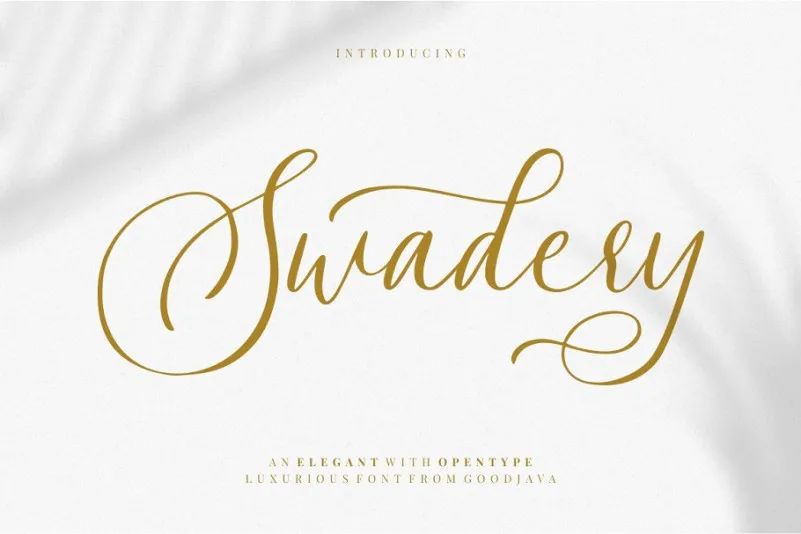
Swadery Script Font – Download Grátis
Esta é uma fonte script moderna e elegante ideal para aqueles que buscam uma mistura perfeita de elegância e naturalidade em seus designs. Intitulada Swadery, esta fonte foi criada pela Good Java Studio como uma opção perfeita para diversas necessidades de design gráfico. Swadery é um script moderno e autêntico que combina elementos de escrita à mão com tendências contemporâneas. Perfeito tanto para criar logotipos, cartas devidas, embalagens de produtos ou até mesmo para anúncios e postagem em redes sociais, Swadery é uma escolha ideal. Suavemente prática para uso em etiquetas, fotografia, marcas d’água, eventos especiais ou qualquer outro projeto que exija um toque elegante e autêntico. Através do Swadery Script Font, você obterá uma opção de letra perfeita para criar designs memoráveis. Suas linhas suaves e acentos distintivos permitem que sua mensagem seja notada e gravada na memória dos seus clientes. Seja por suas aplicações em design gráfico ou publicidade, Swadery é uma fonte indispensável que vai reforçar a presença de marca do seu projeto ao longo do tempo.